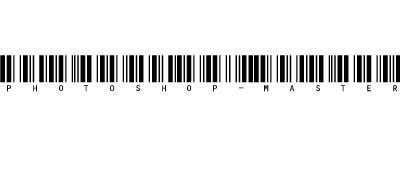
Прикольно)
посмотрим что за он
Афигенный шрифт!
Это шрифт:
Slipknot - People Shit
Крутой шрифт))
не плохо можно так поугарать будет )
Действительно не плох...да пригодится !!!!!!!!то что искал!!!!!!!!!!!!!!!!!!!!!!!!
вау класс
пригодился же)))
Интересно, зачем вы ставите шрифты, если нет поддержки русского языка?